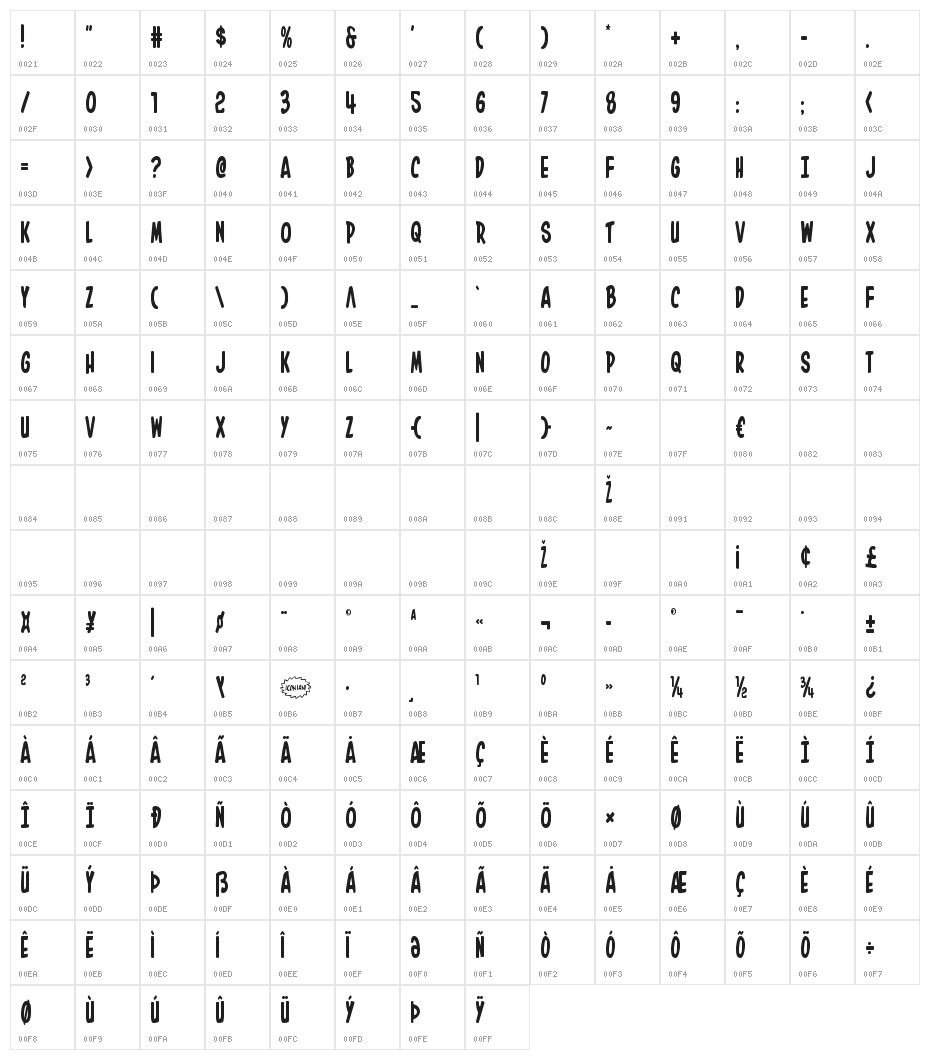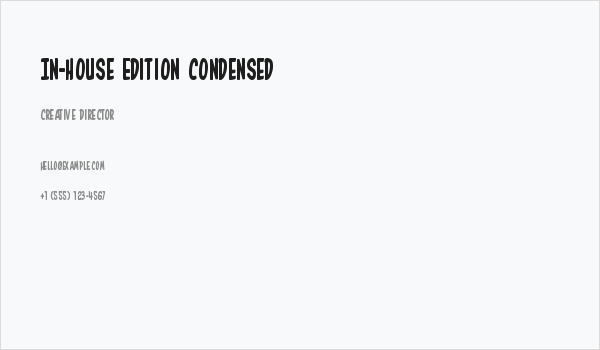
In-House Edition Condensed Font
✎ Comic
| 整体风格 | Playful and Whimsical |
| 推荐项目 | Ideal for children's books, playful posters, creative branding, and informal invitations. |